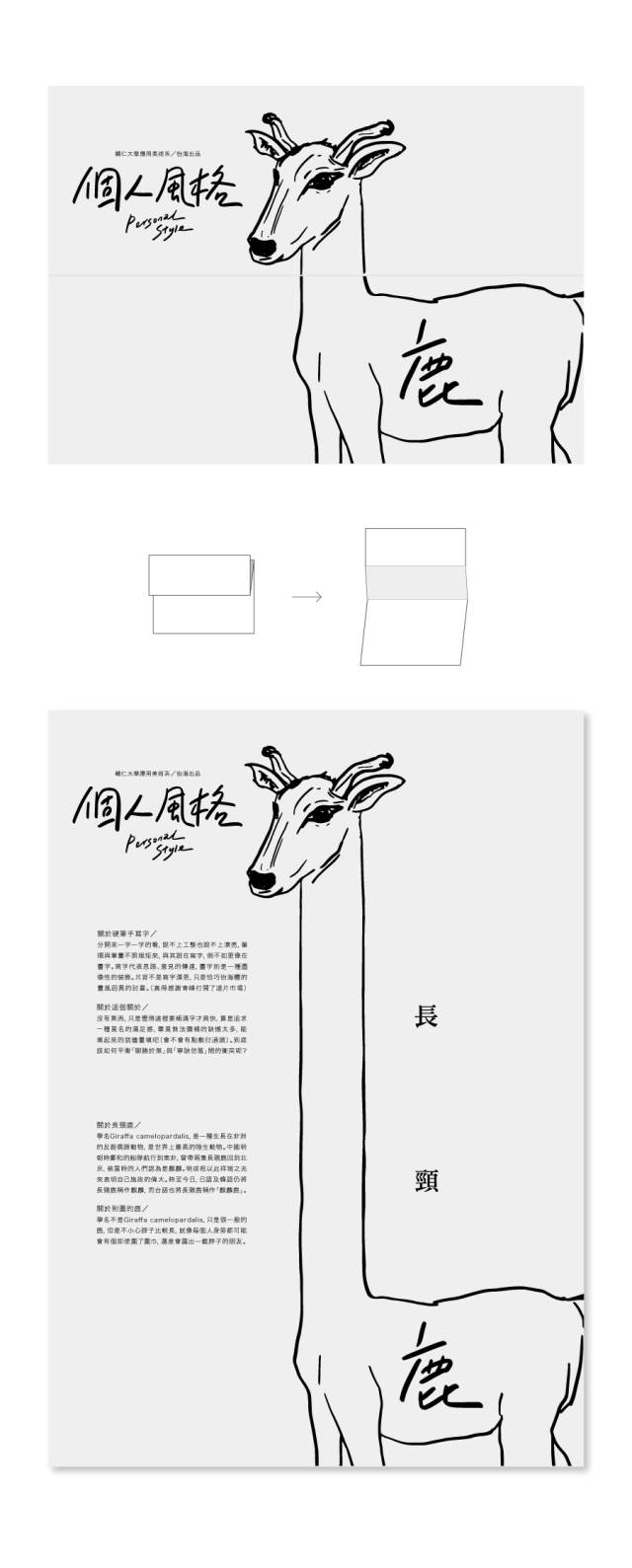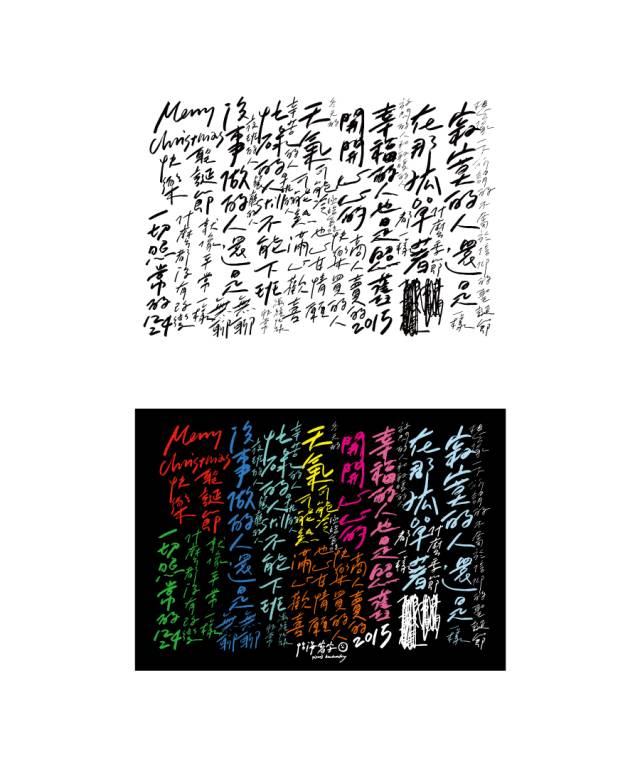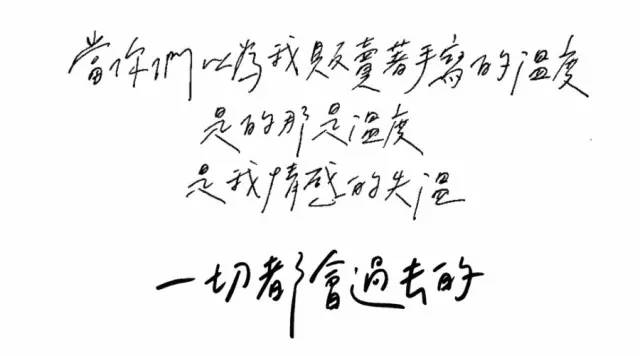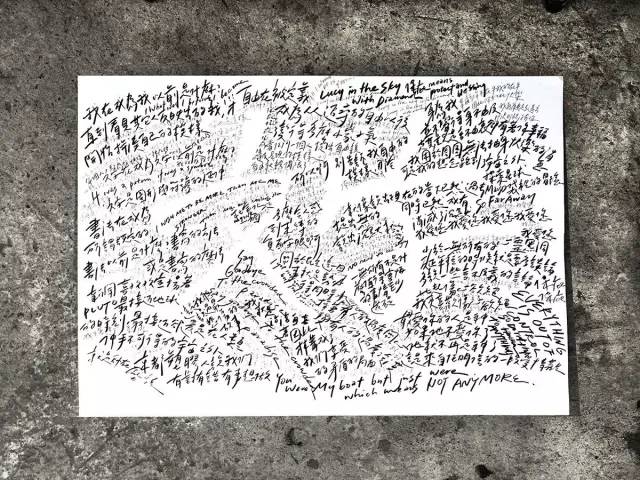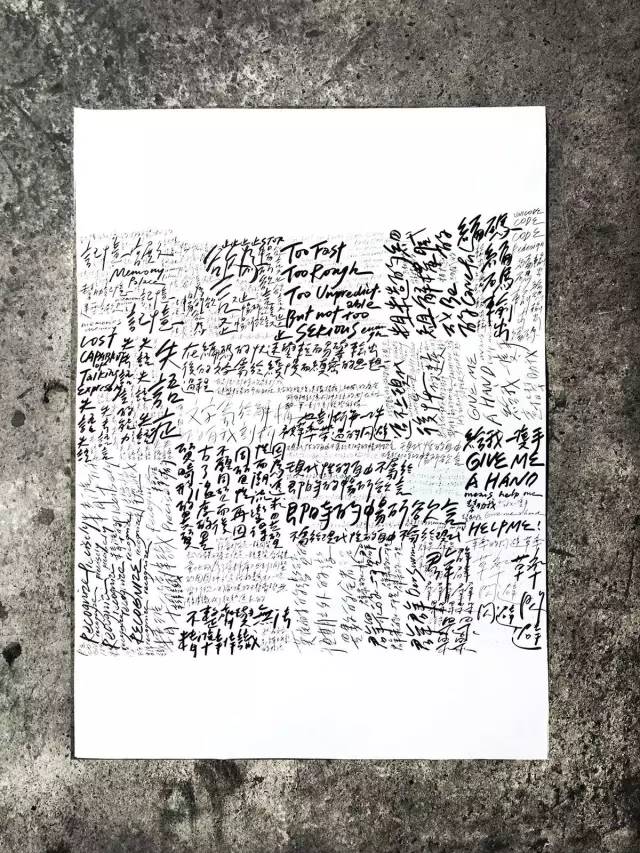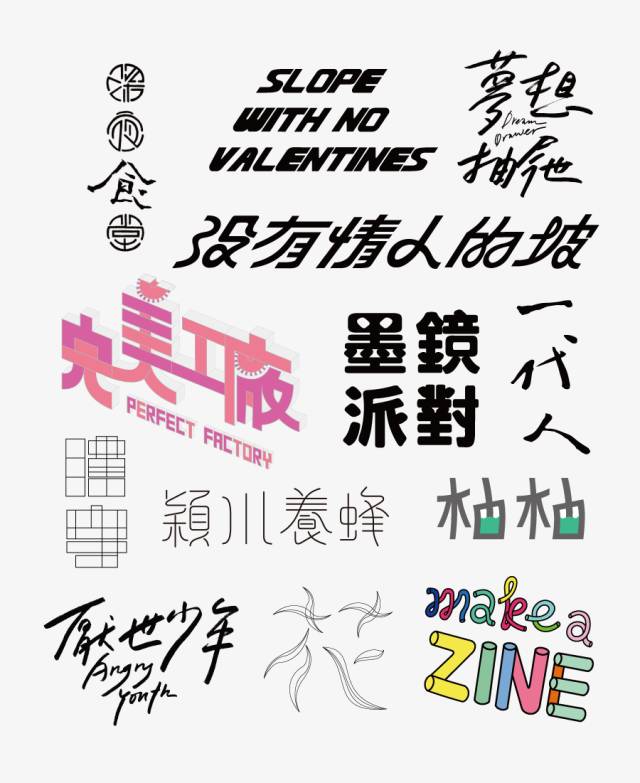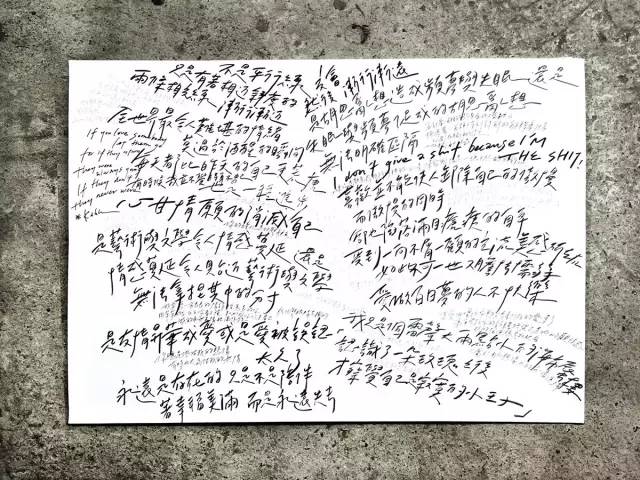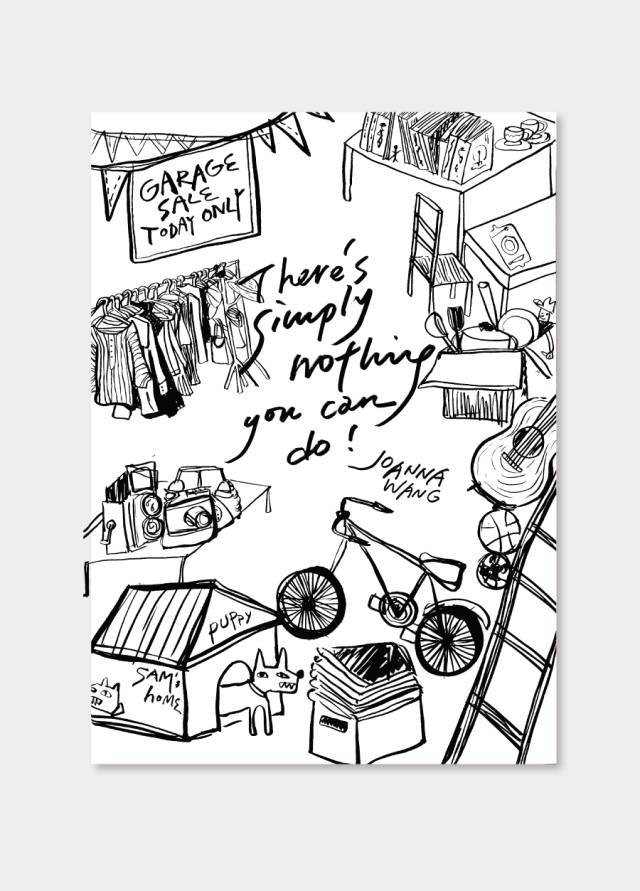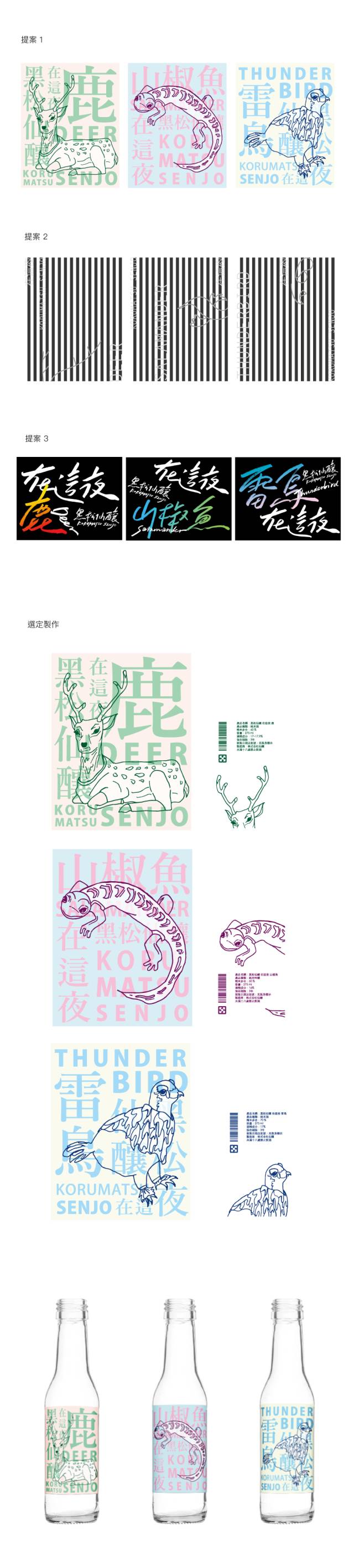
手写字体的设计案例和使用场景
当你们以为我是贩卖着手写的温度,
是的那是温度,
是我情感的失温。
怡海,来自台湾的设计师,毕业于辅仁大学应用美术系。今天要介绍的是他的作品,特别是手写字和字体设计。
听听他自己怎么说的。
关于硬笔手写字/
分开来一字一字的看,说不上工整也说不上漂亮,笔画不按规矩来,与其说在写字,倒不如更像在画字。写字代表思路、意见的传达,画字则是一种图像性的装饰。其实不是写字漂亮,只是恰巧怡海的画风诡异的讨喜。
关于这个关于 /
没有担心,只是觉得这里要补满字才爽快,算是追求一种莫名的满足感,毕竟无法弥补的缺憾太多,能填起了的就尽量填吧。
随心所欲的手写字
一些字体设计作品
>單位:沒有情人的坡
活動:輔大週三派對
Party/ Slope With No Valentines
Sake Label/ 黑松仙釀, 在這夜
我个人特别喜欢这组作品
Poster/ Simply Nothing You Can Do
文字造形/ Chinese